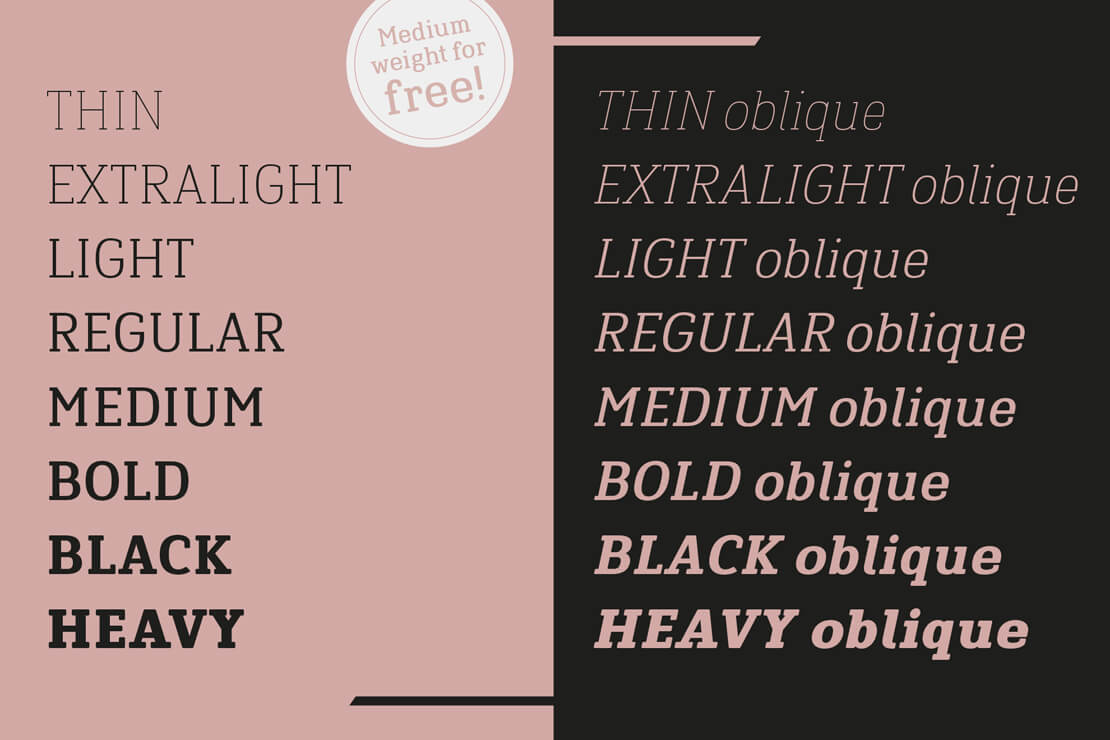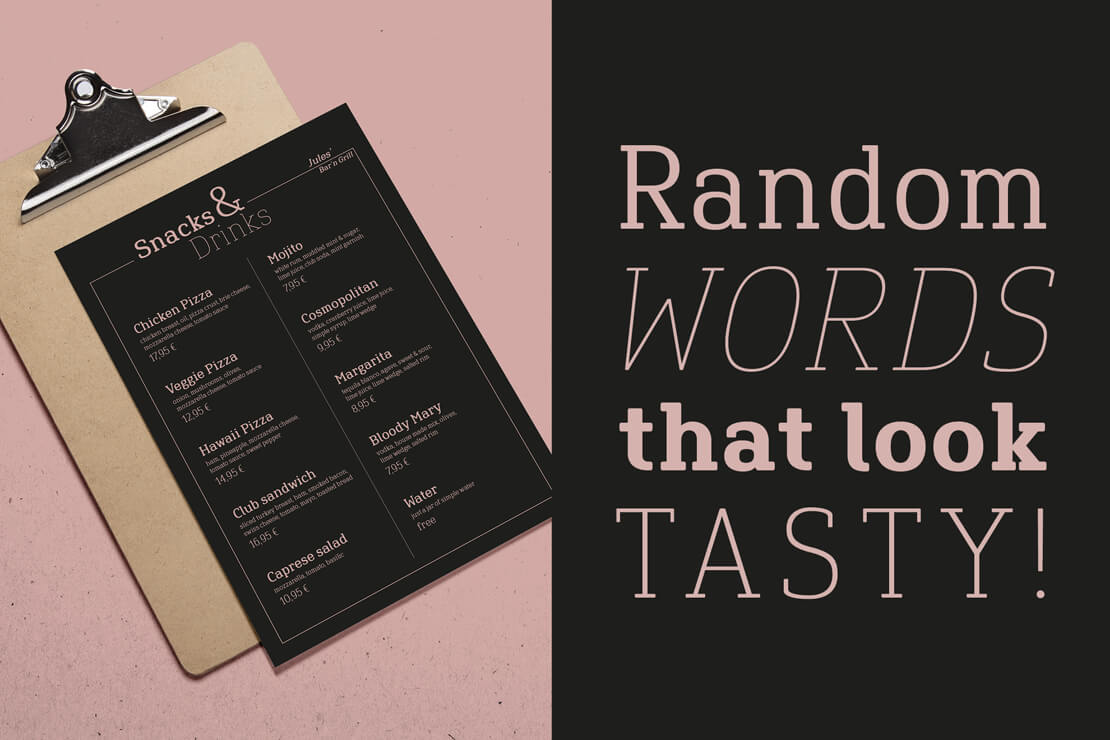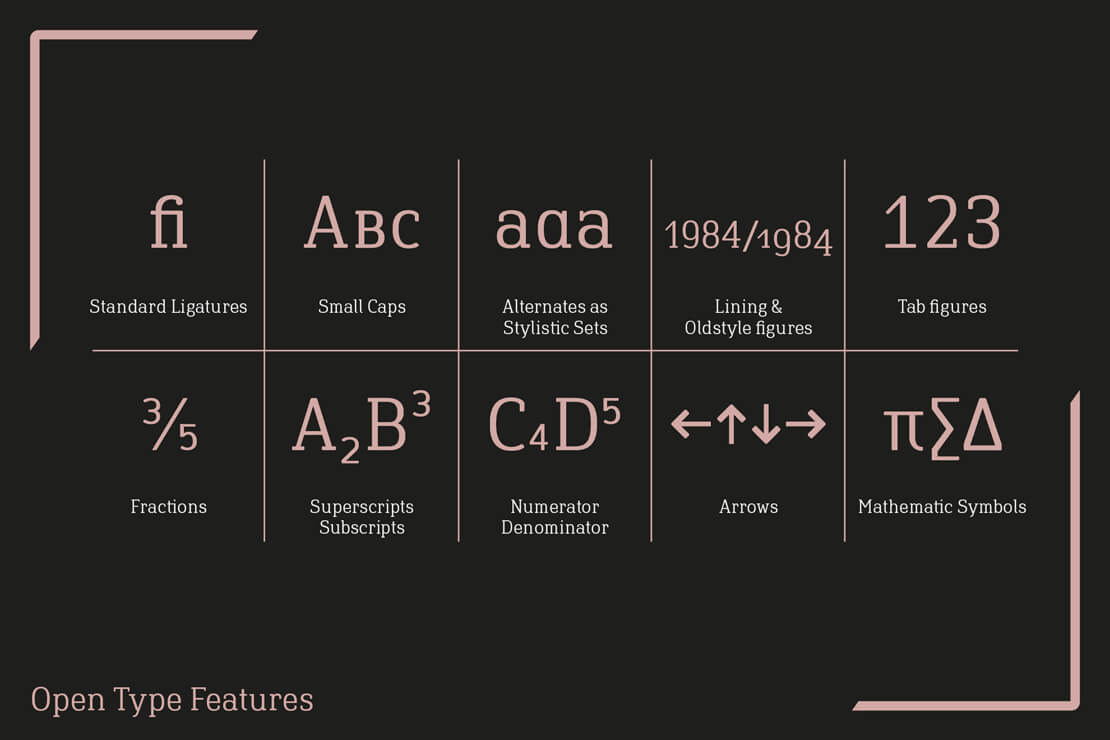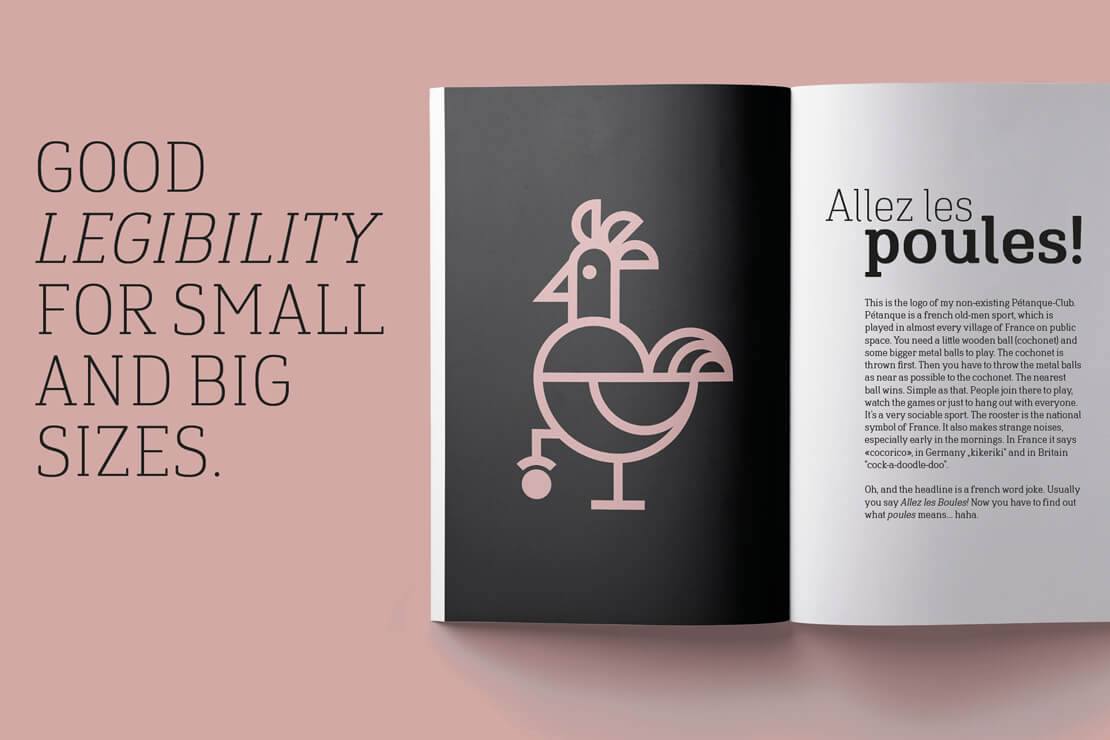
»Finador Slab« von Julien Fincker
Nach der »Finador Sans« erscheint nun auch die Schriftfamilie »Finador Slab« von Julien Fincker. Sie wurde entwickelt, um der Sans-Familie einen charakterstarken Partner an die Seite zu stellen, ohne dabei die Grundeigenschaften von Funktionalität und Freundlichkeit zu verlieren.
Aufgrund ihrer Charakterstärke ist »Finador Slab« geeignet für Editorial, Branding, Packaging und markante Logos und bietet zudem in der Anwendung viele weitere Möglichkeiten.
Die Schriftfamilie besteht, ebenso wie die Sans, aus 8 Gewichten, von Thin bis Heavy, plus der passenden Kursiven. Mit 900+ Glyphen pro Schnitt werden über 200+ lateinbasierte Sprachen abgedeckt. Beinhaltet ist zudem ein erweitertes Set an Währungssymbolen und weitere Open Type Features wie Small Caps, Ligaturen, Ziffernvariationen, automatische Brüche etc.
»Finador Slab« ist ein vielseitiger Allrounder, der für Fließtext, Headlines, Print und Screen eingesetzt werden kann. Die Schrift kann mit dem kostenlosen Medium-Schnitt getestet werden.